О шрифте
Кроме английского, существуют и другие языки.
Чтобы вы понимали: пригодность книги для кириллицы не доказана. Адаптация присутствует только в мелочах (типа буква «д» похожа на дом).
Книга «О шрифте» мне встретилась в подборке книг для дизайнеров. Передо мной часто стоит задача, какой шрифт выбрать для заголовков и текстов на слайдах, и я очень надеялась, что книга хоть как-то мне в этом поможет. Вывод у меня получился следующий: полагайся на свои глаза. Всё, все правила и технические подробности в этом не помогут. Дизайн — вещь субъективная.
Первые процентов 35 книги прошли в недоумении: что такого хорошего в книге, почему ее включают в подборки и хвалят? Затем я зашла на LL почитать рецензии. Ожидаемо было то, что читателей и рецензий у книги мало — все-таки она довольно специфичная. Половина отзывов была восторженными и неконкретными, половина — расстроенными. Я мысленно присоединилась к последним. Согласилась с тем, что книга — вода водой, а полезной информации в ней раз-два и обчелся.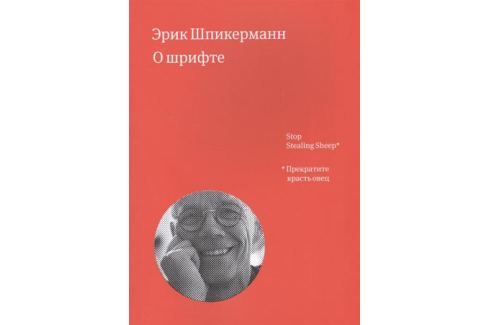
И тут мои глаза на счет этой книги немного открылись. В ней действительно есть полезная информация. Так, третью и пятую главы я советую всем прочитать, на мой взгляд, они самые насыщенные и полезные. Бессмысленных картинок, цитат непонятных людей и персонажей, вырвиглазного красного тут действительно много, и за ними так сложно усмотреть важное. В основном тексте по большей части метафоры о шрифтах, а комментарии оказались информативными.
Главная ошибка автора, на мой взгляд, состояла в отсутствии целевой аудитории. Я так и не поняла, для кого книга. Экскурс в дизайн в разрезе шрифтов — может быть, но.. минусы были выше. Для профессионалов — они и так все это знают. Для тех, кто хочет стать профессионалами — для них другие книги есть, более технические и сухие, с хорошей структурой, понятным описанием терминов.
Здесь на тебя почти что с неба валят термины, значение которых приходится либо гуглить, либо додумывать исходя из слова. И автор об одной и той же теме рассказывает в разных главах, приходится информацию собирать как бисер. Например, про то, каким должен быть шрифт для текста, который будут часто читать, было в трех-четырех главах.
Сложно однозначно сказать, стоит читать всю книгу или нет. Конспект помещаю под кат. Свои мысли выделю курсивом, их можно пропускать. Надеюсь, издательство МИФ меня не забанит. Стоп, им же негде меня банить.
Журнал «Шрифт» • Эрик Шпикерман в мастерской p98a
«Нам просто нравится печатать» — такими словами встречает первый номер журнала Paper, который Эрик Шпикерман c небольшой командой выпускает в мастерской p98a.
Эрик, вопрос для разогрева.
Вы — определённо рок-звезда для многих дизайнеров, а кто из дизайнеров был или остаётся рок-звездой для вас?
О боже, вот так вопрос… Ну, я могу назвать одного действительно важного для меня человека. Я работал с Гюнтером Герхардом Ланге. Мы познакомились, не помню точно, где-то в 1960-х годах. Я посещал его курс по типографике, пока он преподавал в Берлине. Затем он переехал в Мюнхен, а я стал работать над заказами для его словолитни Berthold.
У меня была своя печатная мастерская, которая сгорела в результате несчастного случая в 1977 году. Я использовал там старые шрифты вроде Lo-Type и Block, и после этого происшествия мне захотелось их сохранить. Я подумал: почему никто не приспособит всё это добро для фотонабора — уже широко распространённой в 1970-х технологии? Так что я начал с адаптации старых шрифтов к фотонабору; разумеется, дело было ещё до всякой цифры.
Гюнтер Герхард Ланге (Günter Gerhard Lange, 1921–2008) преподавал практически до конца своих дней. Он читал лекции с большим энтузиазмом и страстью, что очень вдохновляло и собирало молодёжь вокруг него. Ланге открывал студентам глаза на искусство, архитектуру, литературу и типографику. Он неустанно подчёркивал важность образования и любви к своему делу, говорил о необходимости внимания одновременно к деталям и целому. —
В то время я жил в Лондоне, и, когда Гюнтер, не говоривший по-английски, приезжал туда, я был кем-то вроде его переводчика и помощника. Впоследствии мы подружились, и в начале 1980-х он, собираясь уйти на покой, предложил мне стать его преемником — художественным руководителем в Berthold. Мне это было не по душе: во-первых, к тому моменту уже появились «Маки» — дни Berthold и фотонабора были сочтены. Во-вторых, я понимал, что никто на самом деле не мог бы стать преемником Гюнтера. Он был не просто дизайнером, он был по-настоящему выдающейся фигурой и великим оратором. В общем, я отклонил это предложение. Он был очень огорчён — настолько, что в течение пары лет обращался ко мне «господин Шпикерман», хотя до этого мы почти 20 лет называли друг друга по имени, что, кстати, довольно редко в Германии. Он подчёркивал таким образом, что нашей дружбе конец.
Можно ли сказать, что опыт работы с Ланге сформировал ваш подход к шрифтовому дизайну в целом?
Дело не в подходе, ты просто работаешь и внимательно следишь за тем, что важно. Кроме того, тебе нужно знать кое-что из истории, иначе ничего не выйдет. Возможно, сегодня это уже старомодная точка зрения. Ланге, в отличие от Геррита Ноордзея, был далёк от теории письма, хотя и занимался каллиграфией в университете. С другой стороны, он не принадлежал и к популярной в то время школе Германа Цапфа. Честно говоря, они просто друг друга не любили. Ланге очень хорошо знал историю, хоть и, как большинство людей его поколения, не говорил по-английски или по-французски.
В конце 1980-х Шпикерманн и его вторая половинка, Джоан Шпикерманн, запустили FontShop. Это был первый производитель и распространитель электронных шрифтов по почте. Было создано расширение компании под названием FontShop International, которое занимается публикацией линейки шрифтов FontFont.Кроме того, Шпикерманн получил звание почетного профессора Академии художеств в Бремене. Колледж дизайна Art Center в Пасадене присвоил ему звание почетного доктора за его ценный вклад в графический дизайн. Он также является членом правления Немецкого совета по дизайну. В 2001 году он переработал британский журнал The Economist . В следующем году он опубликовал свою книгу о шрифтах под названием «Хватит красть овец и узнайте, как работает шрифт» для Adobe Press.Позднее книга была опубликована на нескольких других языках, включая португальский, немецкий и русский.